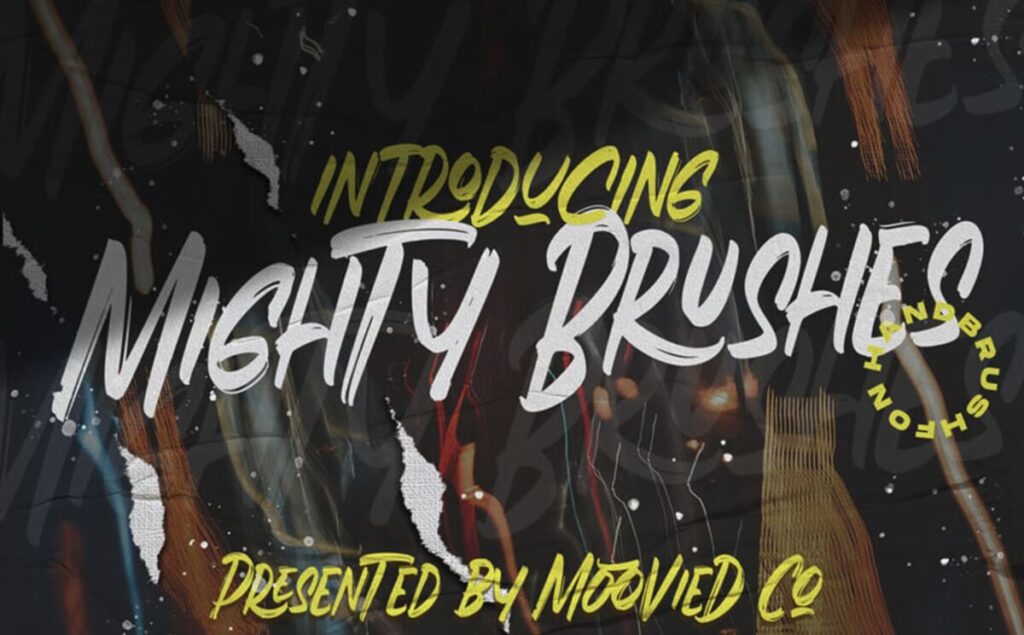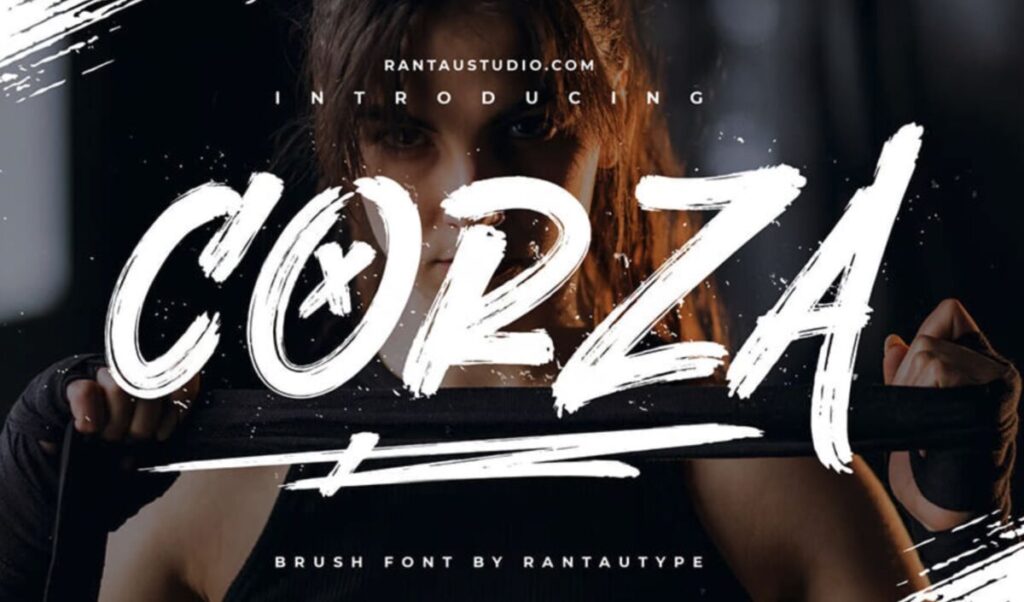
60 e oltre Font Brush per Poster: Una Collezione Creativa per Design Impattanti
L’articolo di Graphic Design Junction presenta una vasta selezione di oltre 60 font brush, ideali per elevare il design di poster e altri progetti creativi. Questi font, dinamici e stilisticamente accattivanti, sono perfetti per creare poster unici che catturano l’attenzione.
Caratteristiche e Utilizzo dei Font Brush
I font brush si distinguono per il loro aspetto dinamico e la capacità di aggiungere personalità e stile a qualsiasi progetto. Sono particolarmente adatti per:
Poster: Creazione di poster per eventi, promozioni o celebrazioni.
Branding: Sviluppo di loghi e materiali di branding che esprimano energia e creatività.
Progetti Personali e Professionali: Aggiunta di un tocco artistico a inviti, biglietti da visita, presentazioni e altro ancora.
Esempi di Font Brush Menzionati
L’articolo include una vasta gamma di font brush, ognuno con il suo stile unico. Alcuni esempi degni di nota sono:
Batteny Brush Font: Un font script elegante con texture brush, perfetto per progetti di branding professionali.
Mighty Brush Font: Un font brush script ideale per stampe, loghi, inviti e social media.
Corza Brush Font: Un font brush autentico con imperfezioni fatte a mano, adatto per watermark, loghi e copertine di album.
Jopersag Brush Font: Un font sportivo e audace, perfetto per progetti di branding nel settore sportivo.
Nirmana Brush Font Wedding: Un font calligrafico ideale per inviti di matrimonio e progetti correlati.
ELEMENT Brush Font: Un font brush con tratti ruvidi e decisi, perfetto per progetti che richiedono un tocco energico.
Versatilità e Applicazioni
Questi font sono versatili e adatti a una vasta gamma di progetti, tra cui:
Poster per feste di Natale ed eventi aziendali.
Flyer per celebrazioni del Nuovo Anno.
Materiali di marketing e branding.
Progetti di design personale.